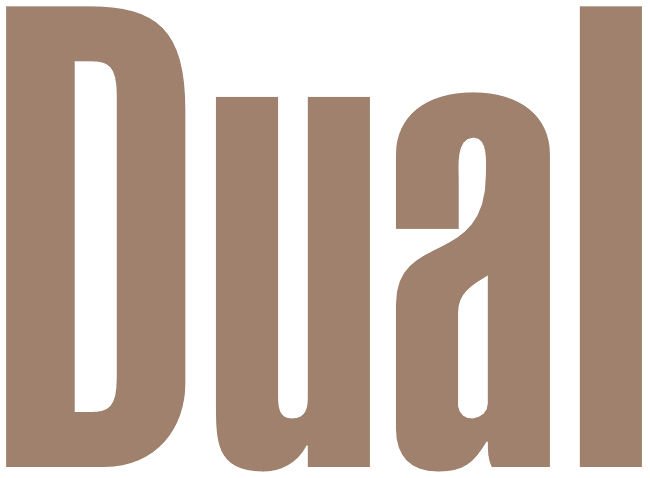
Welche Schrift hat DUAL benutzt?
Welche Schrift hat DUAL Gebrüder Steidinger, der legendäre (u.a.) Plattenspieler-Produzent aus dem Schwarzwald benutzt?
WhatTheFont liefert keine brauchbaren Ergebnisse.
Das ist bestimmt modifiziert. Die Grundlage war wahrscheinlich eine Helvetica Ultra Compressed.
Helvetica Ultra Compressed:
Compressa:
Dual (Aus einer Bedienungsanleitung gescannt)
So einfach ist es dann doch nicht.
Dann wäre es auch kein Logo. In den seltensten Fällen wird Schrift unverändert für ein Logo verwendet.
Aus welchem Grund fragst du nach der »Schrift«?
In der Zeit, als das Logo entstand, wurden selbige normalerweise speziell für diese Anwendung gezeichnet. Man nahm nicht einfach eine Schrift, weil Satzschriften nur in bestimmten Größen verfügbar waren. Man konnte sie also nicht setzen, vektorisieren und als Logo verbreiten. Mehr als »ähnlich« wirst du also kaum bekommen.
Ich denke, dass du keine Satzschrift finden wirst, die exakt dem Dual-Schriftzug entspricht. Wenn man sich bspw. den oberen Bogen des a anschaut, sieht man, dass dort keine optischen Korrekturen vorgenommen wurden. Bei (gut gemachten) Satzschriften treten solche Fehler eher selten auf.
Nach der Schrift frage ich, weil mir die gut! gemachten Buchstaben – trotz ihrer »Fehler« über die ich hinweg sehe – gefallen und ich sie gerne benutzen möchte. Das Logo taucht in der Form ca. 1960 zum ersten mal auf einem Dual 1008 auf. Nun habe ich – natürlich falsch – assoziiert: Da ja z.B. auch die angesprochene Helvetica heute für viele Logos (unverändert) benutzt wird, könnte es damals eben auch so gewesen sein. Aber jetzt weiß ich: das ist so auf gar keinen Fall vorgekommen, weil es ja schon lange her ist.
Vermutlich habt ihr recht und das Logo wurde von irgendeiner Sekretärin, die gerne Pferde gemalt hat, gezeichnet. In den 60ern war so etwas ja noch möglich ;)
... und die konnte froh sein, da sie eine Festanstellung, wenn auch nur als Sekretärin, hatte - heute machen sowas freischaffende Nerds über myHammer & Co ...
Ernsthaft:
man wird sich schon an einer Schrift orientiert haben, und das wird wohl die Helvetica, die damals neu und voll hipp war, gewesen sein. Bei 4 Buchstaben ist eine Neuzeichnung und Anpassung auch wesentlich einfacher als z. B. bei ›Lufthansa‹ oder ›Deutsche Bank‹ (ach ne, das war die andere).
Ja, natürlich — und bis 1970 haben wir auch alle noch auf Bäumen geschlafen...